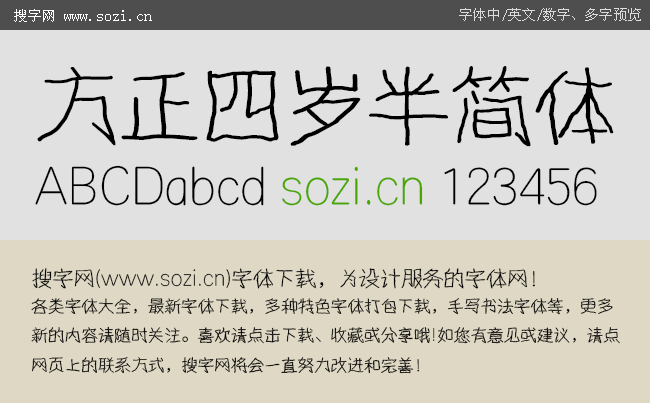
方正四歲半簡(jiǎn)體手機(jī)字體包
搜字網(wǎng)給大家提供一款方正四歲半簡(jiǎn)體手機(jī)字體包手機(jī)中文字體下載。這款手機(jī)字體是一款卡通手寫(xiě)風(fēng)格的藝術(shù)字體,字形稚氣可愛(ài),充滿(mǎn)童趣,非?蓯(ài)。喜歡的朋友趕快下載吧。